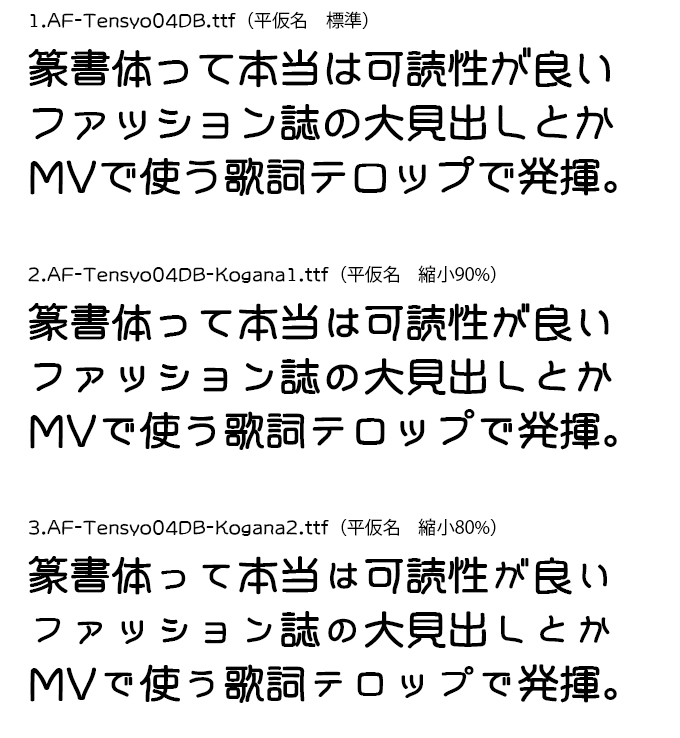
2)AF-Tensyo04DB-Kogana1.ttf 小仮名サイズ90%
3)AF-Tensyo04DB-Kogana2.ttf 小仮名サイズ80%
ファッション誌の見出し用、小仮名版は可読性が変化する事でMusicvideoの歌詞テロップに効果を与えます。アプリケーションソフト利用、動画テロップ後の配信、Web Serverへのアップ、PDFエンベッド、印刷やロゴなど商用利用、個人または同人系インディーズソフト1タイトル、1万ダウンロードまでバンドルできます。(※1)